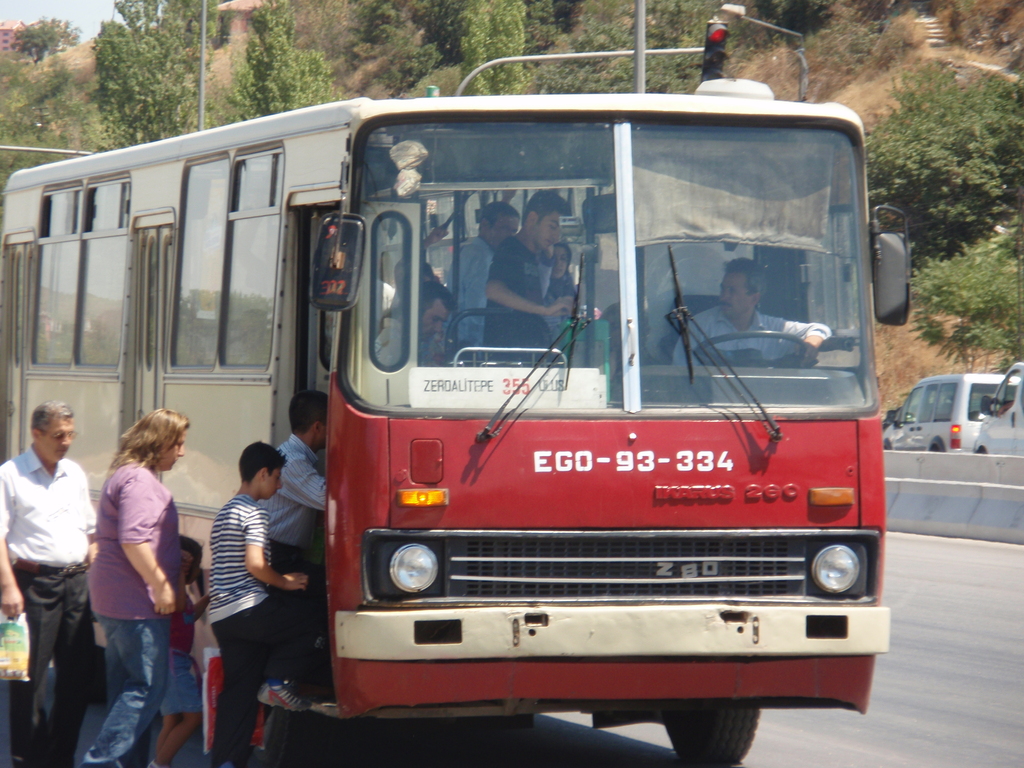
Schwere Frage nach der Schriftart
Auf dem Bild ist ein Ikarus 280 Baujahr 1993 der EGO (Stadtwerke Ankara, Bild von mir als ich im August 2008 dort Urlaub gemacht habe) zu sehen. Außerdem zu sehen, der Linienverlauf auf der Tafel an der Frontscheibe:
LINIE 355: ZERDALITEPE - ULUS
Frage: Welche Schriftart sind diese Zeichen und die Ziffern auf dieser Tafel an der Frontscheibe???
Das sieht nach Handarbeit mit Hilfe von Schablonen aus, aber verschiedene Schnitte der Eurostile (auch unter dem Namen Microgramma bekannt) könnten Vorbild gewesen sein.
der fahrplan selbst könnte arial black sein und die beschriftung überalb des fahrplans, ich
schätze mal das ist die haltestelle, dürfte eine handgemachte schrift sein. beide haben aber
nichts mit der schrift auf dem bus gemeinsam, diese scheint auch handgemacht zu sein.
wie hey schon sagte, eion mix aus eurostile und microgramma.